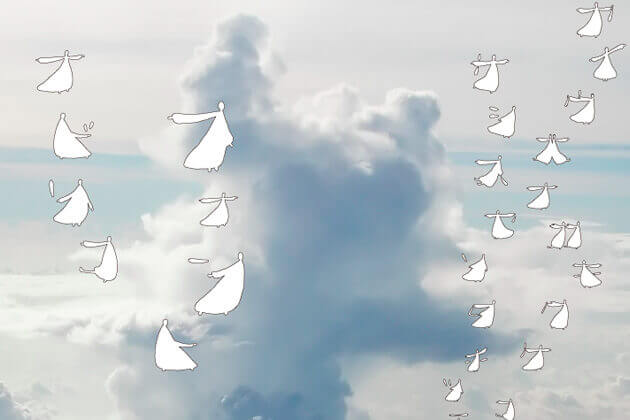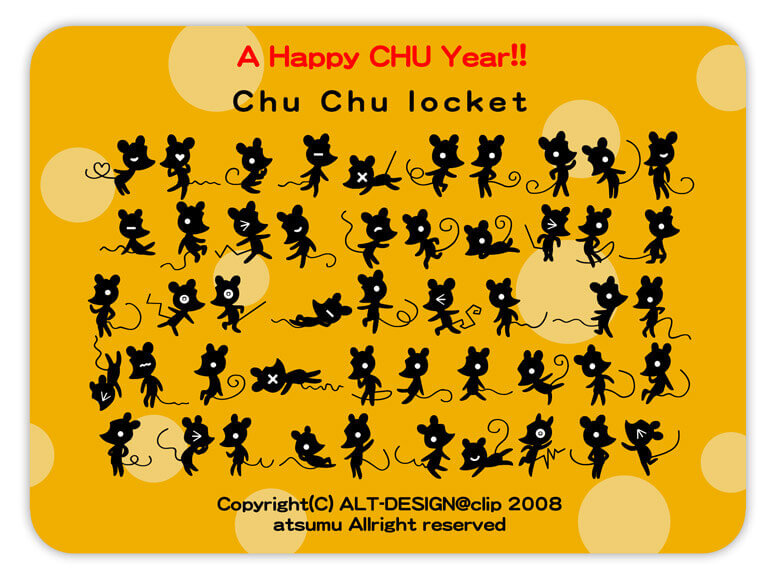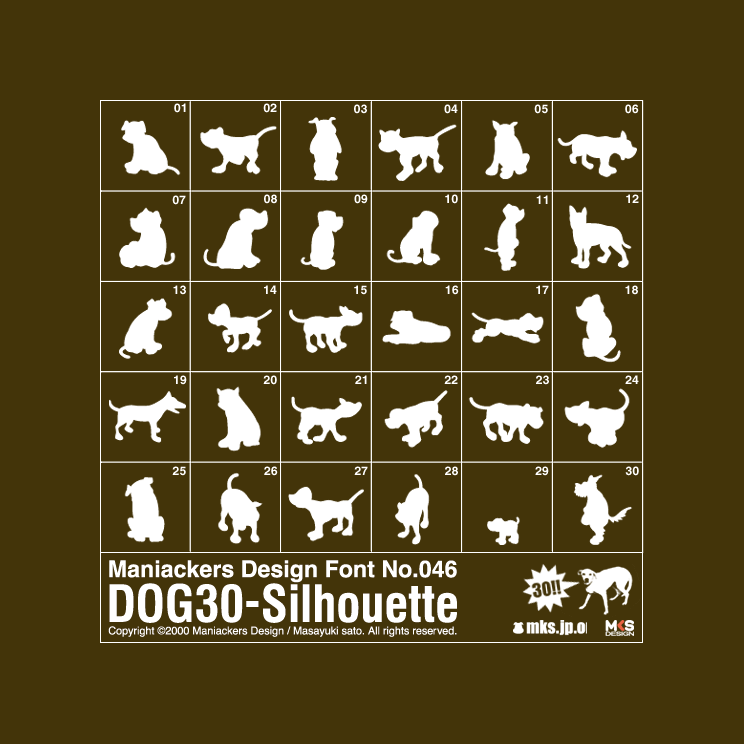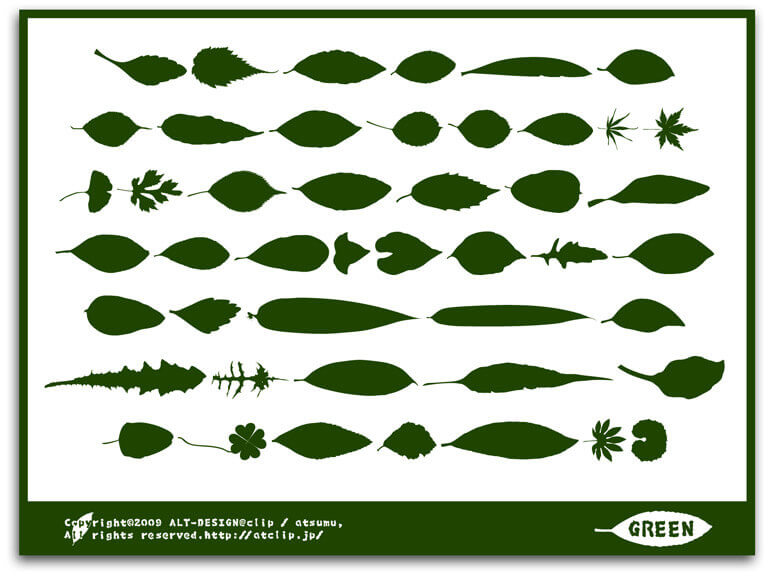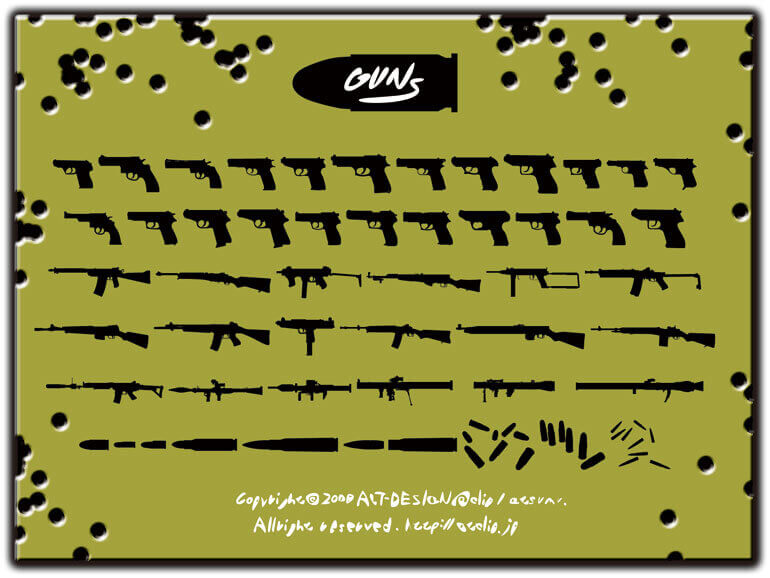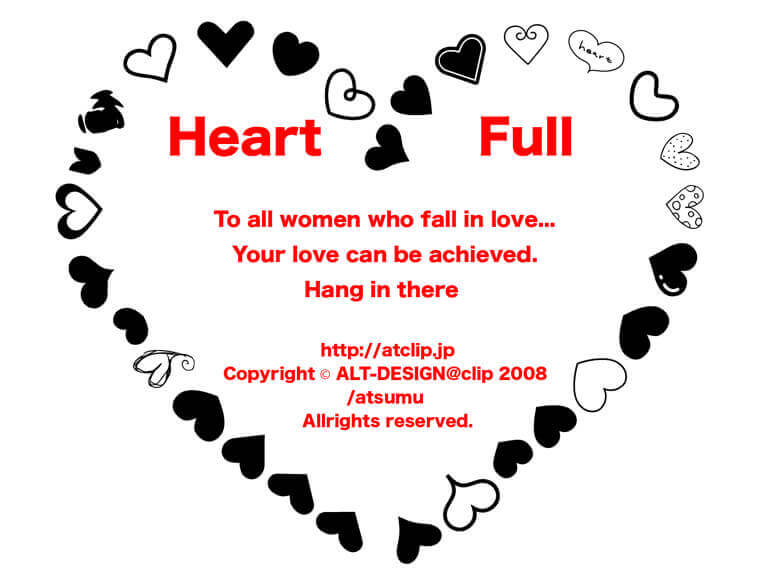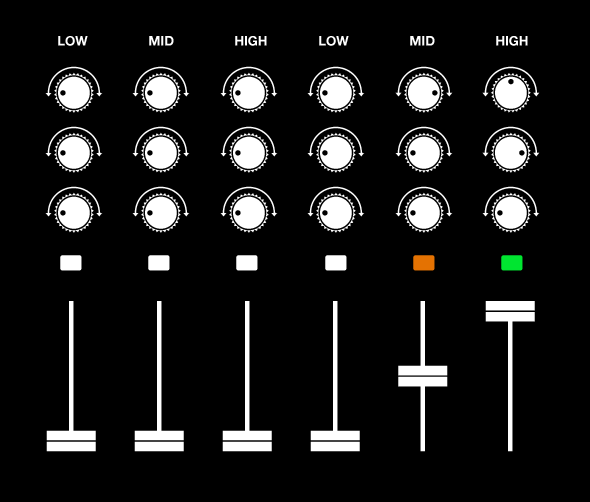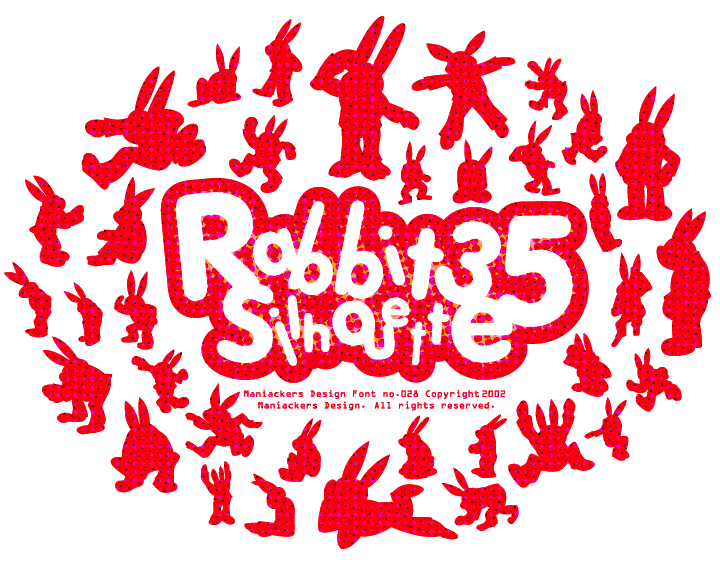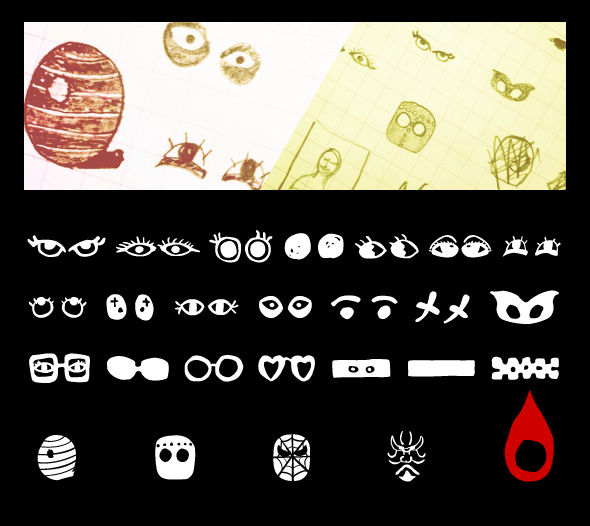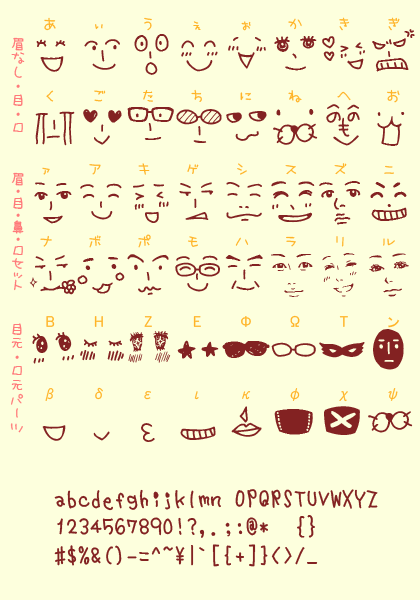
無料でダウンロード可能な絵文字フォント56個まとめ
文字を入力するだけでイラストが表示できる絵文字フォントを56個まとめました。可愛らしい動物から実用的なアイコンまで多彩なフォントをご紹介しています。デザインのアクセントとして使ってみましょう!
01 FontRemix-Type38
38人の多種多様な強者が参加した38文字のフォント。
851手書き雑フォント
「雑」がウリな手書きフォント。現在の収録文字数は34,279文字(スペース除く)。
AK-Headgehogs
可愛らしいハリネズミがイラストとなっているフォント。
AK-keroyon
ケロ好きに使って欲しい、カエルフォント。
AK-MyBaby
幼児向けの可愛らしい絵文字フォント。
AK-Piyoko
紙にマジックで書いたような、ちょっとガタガタしたラインのぴよこちゃんふぉんと。
AK-Uribouz
うりぼうさんフォント。
Character Afro
アフロのビットマップなキャラクターが踊っているフォント。
Chu Chu locket
ネズミがゆかいに踊っているフォント。
DingTheInsect
リアルな虫の絵フォント。
Dog30-Silhouette
イヌのシルエットシリーズフォント。
Emoji Font
ビットマップの絵文字フォント。
EmojiSymbols Font
インターネット上での利用に特化したwebフォント。
FUKIDASHI
文字を入力する感覚で漫画のセリフなどに使える吹き出しを表現できるフォント。
GL-DancingMen
シャーロックホームズ「踊る人形」の暗号文字フォント。
GL-Grimoire-MajKey
ヨーロッパで流布していた魔術書(グリモア/グリモワール)より英国の魔術師マグレガー・メイザースが編集・出版したグリモア「ソロモン王の鍵」に出てくる惑星護符のフォント。
GL-Grimoire-MinKey
ヨーロッパで流布していた魔術書(グリモア/グリモワール)より英国の魔術師マグレガー・メイザースが編集・出版したグリモア「ゲーティア」で紹介されているソロモン72柱の精霊の紋章のフォント。